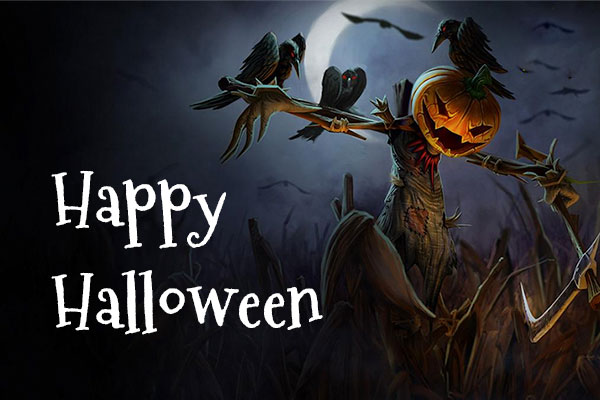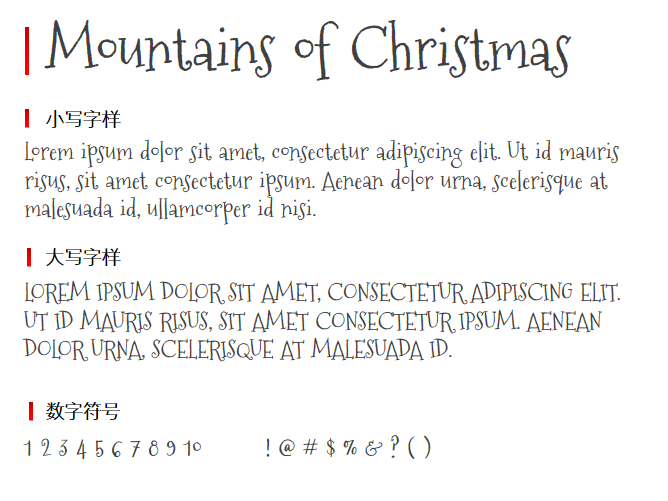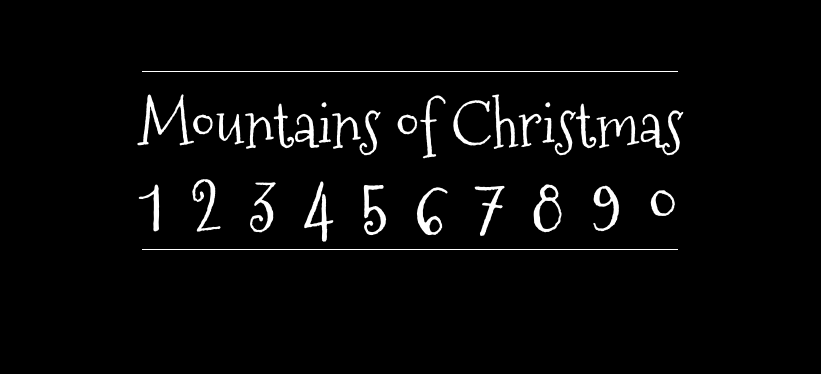
Mountains of Christmas
Mountains of Christmas字体介绍
Mountains of Christmas是国外的Tart Workshop贡献的一款免费商用英文字体,完美的休闲且有趣的哥特风格字体,字形拥有个性的棱角和边角的延伸。该字体拥有2个字重,是一款不可多得的哥特风格英文字体。
Mountains of Christmas字体应用示例